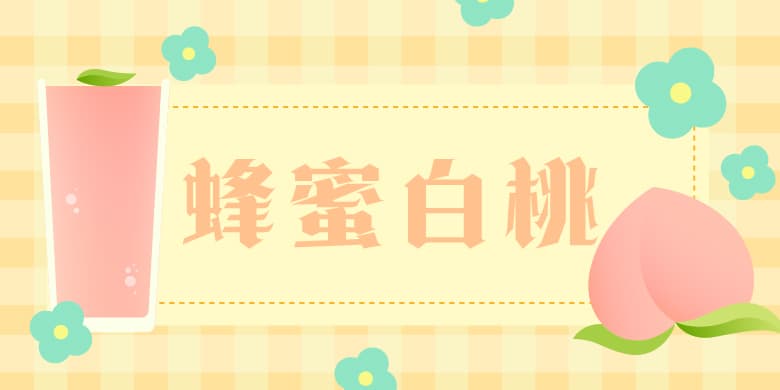
方正诗甜宋家族
品牌:方正字库设计师:郭炳权发行时间:2019字库编码:简繁扩展(GBK)、大陆简体(GB2312-80)分类:创意字体字体属性:精品字
诗甜宋的创意灵感源于钢笔书写的笔形特征,经过提炼整理,使笔画更具规则化。诗甜宋横细竖粗,造型独特,体现出设计宋体的新风格,包含8款不同粗细,适合多种快消品、电子产品等商业宣传和包装设计。